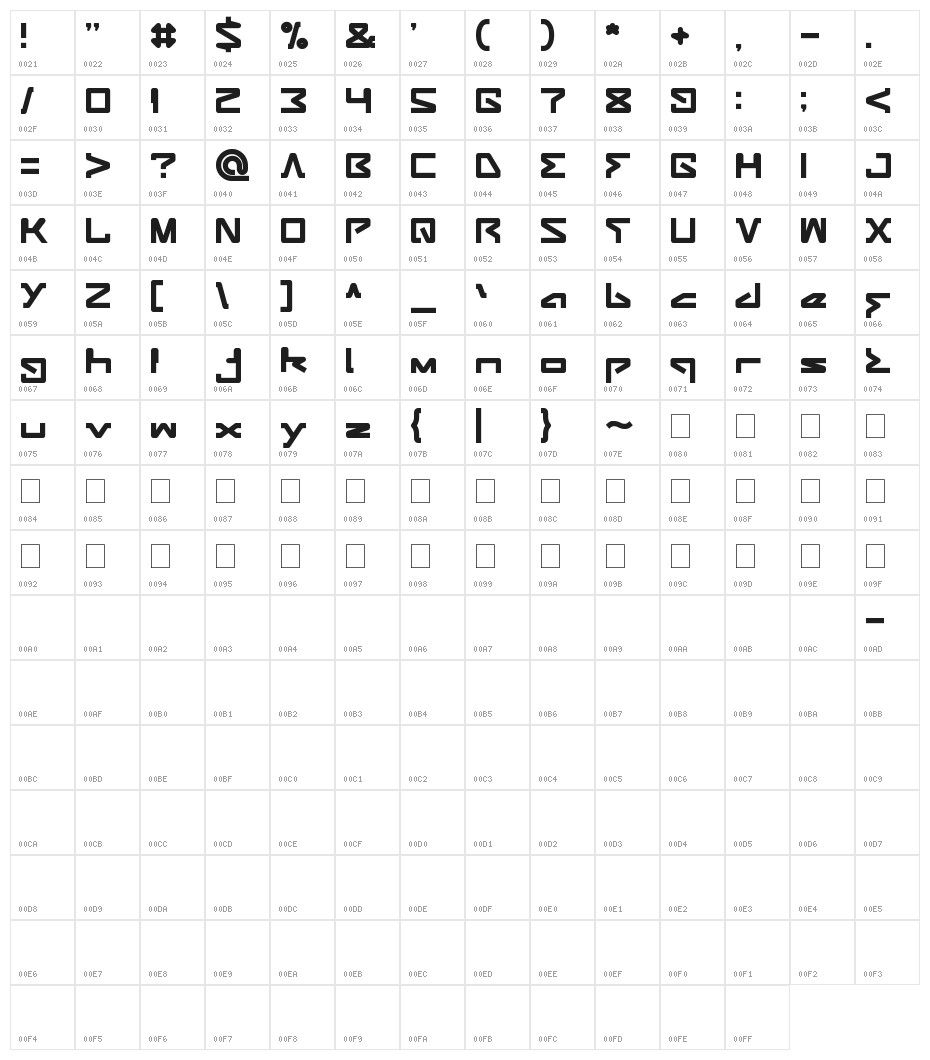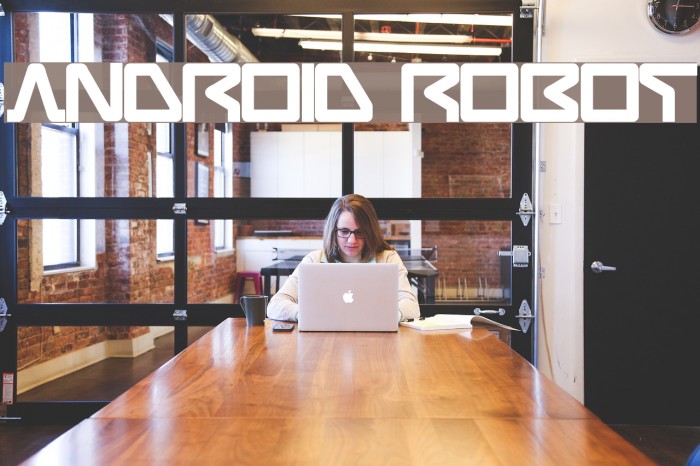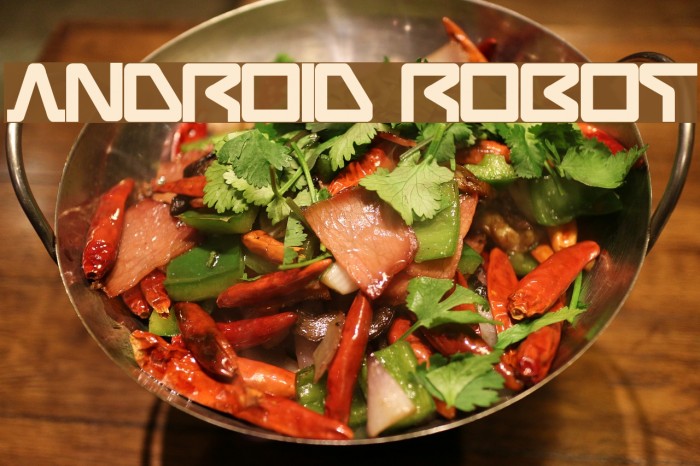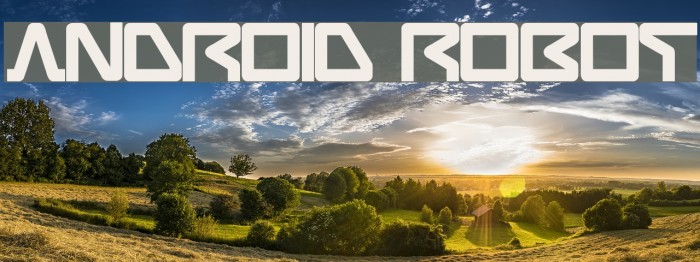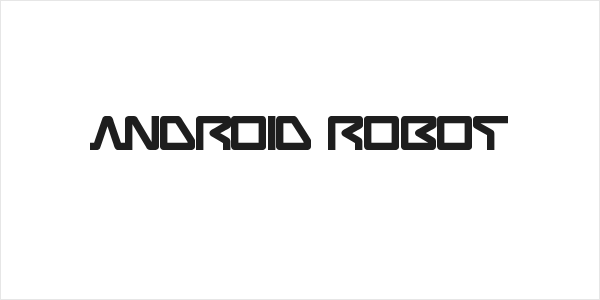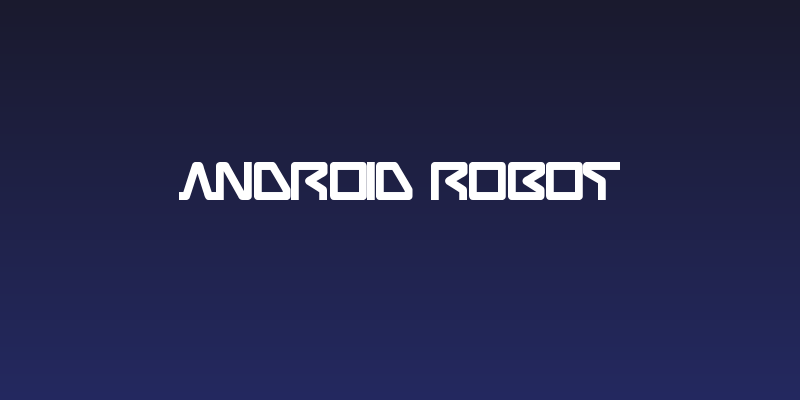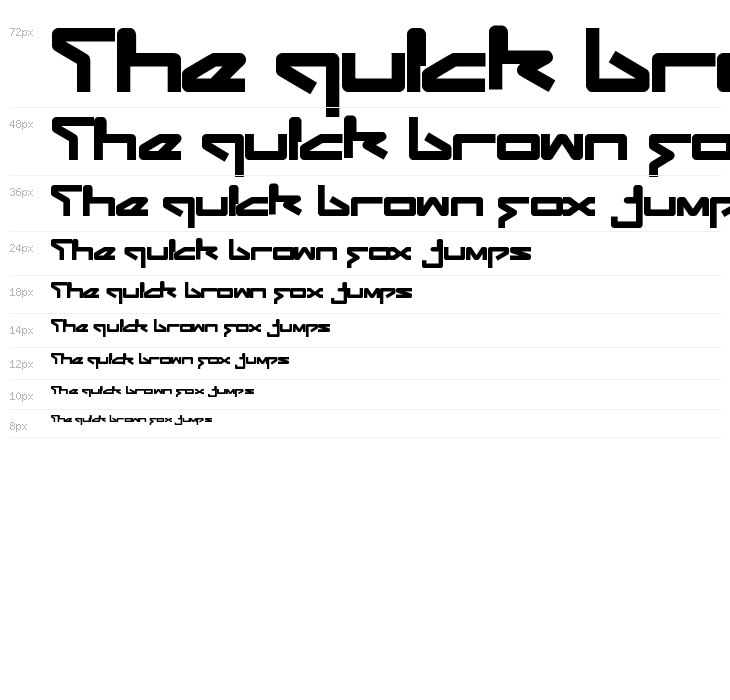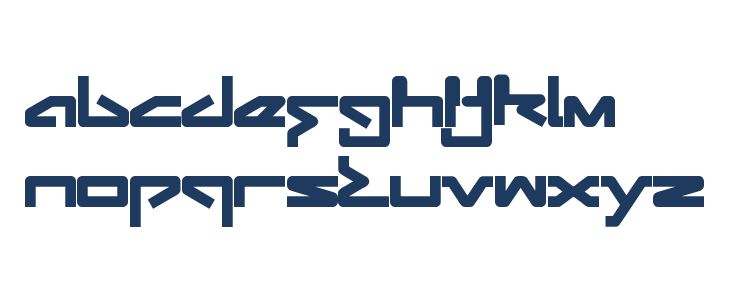
ANDROID ROBOT Font
| Proyectos propuestos | Ideal for technology-themed projects, video game titles, sci-fi movie posters, or any design requiring a modern, digital aesthetic. |